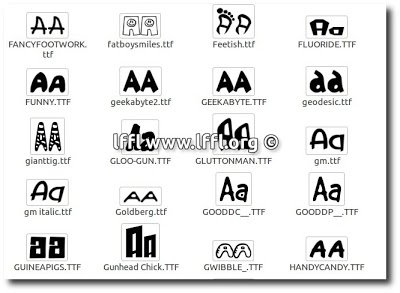
[Raccolta] 177 Fantastici Font dedicati ai Cartoni (Linux - Windows -Mac)
Dobbiamo creare degli inviti per un compleanno o per una festa con amici. Oppure creare un menu per le prossime festività o un biglietto d’auguri di buone feste la prima cosa che sicuramente ci serve per abbellire la nostra creazione è sicuramente un bel font.
Purtroppo nel nostro Sistema Operativo abbiamo installati i classici “professionali” font e siamo alla ricerca di font per rendere più carino il nostro invito. Senza sbattere la testa in ore ed ore di ricerche per la rete LffL ha raccolto per voi ben 177 font dedicati ai cartoni.